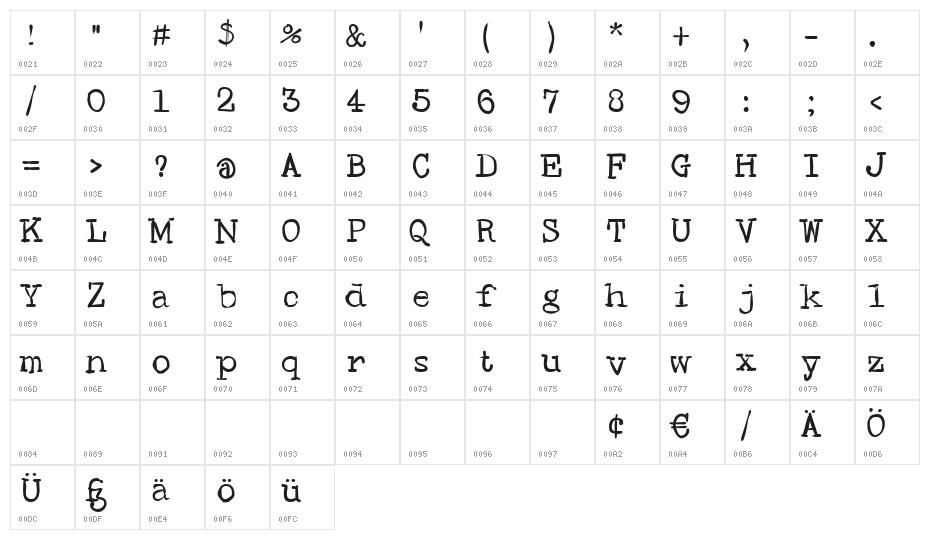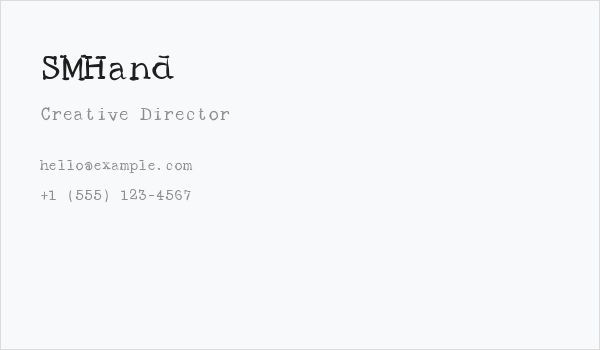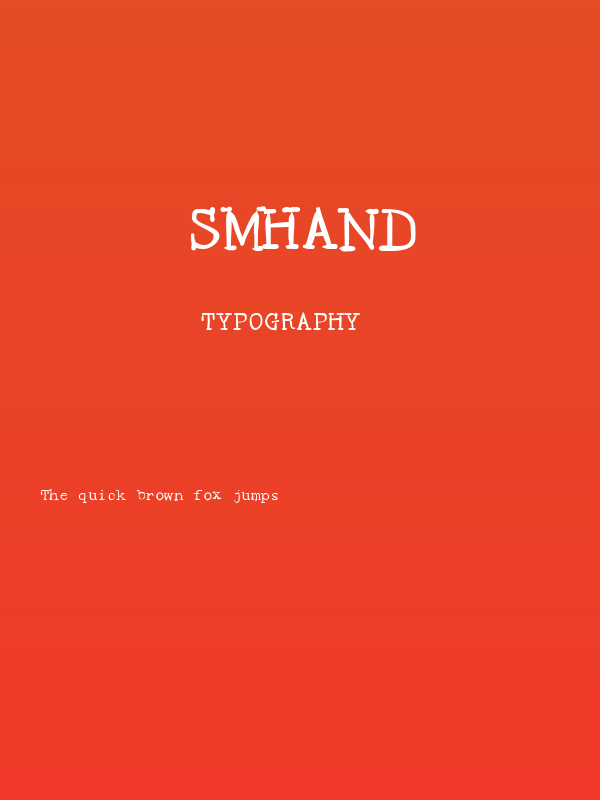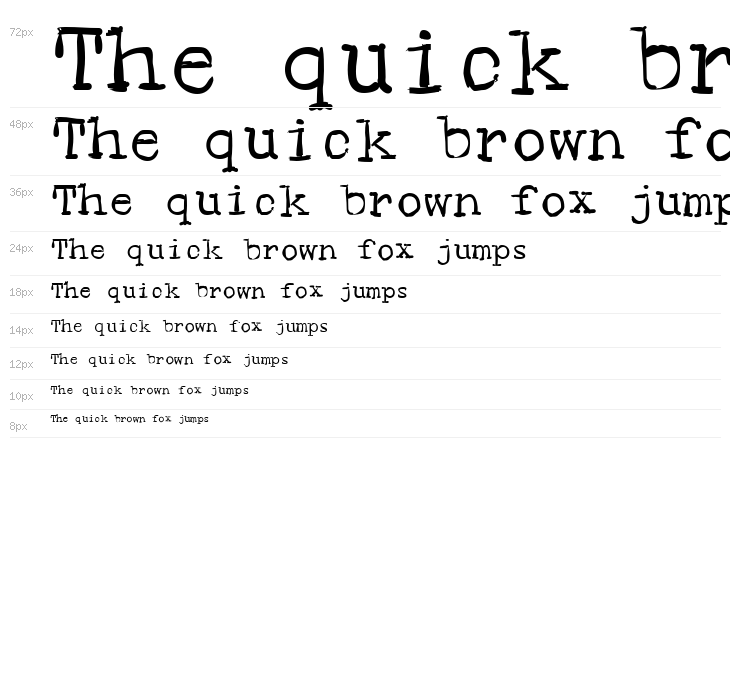
SMHand Font
✎ Typewriter
| 分类 | Typewriter |
| 整体风格 | Vintage |
| 推荐项目 | Ideal for projects requiring a vintage or retro look, such as posters, book covers, or branding materials that aim to convey a sense of nostalgia or creativity. |